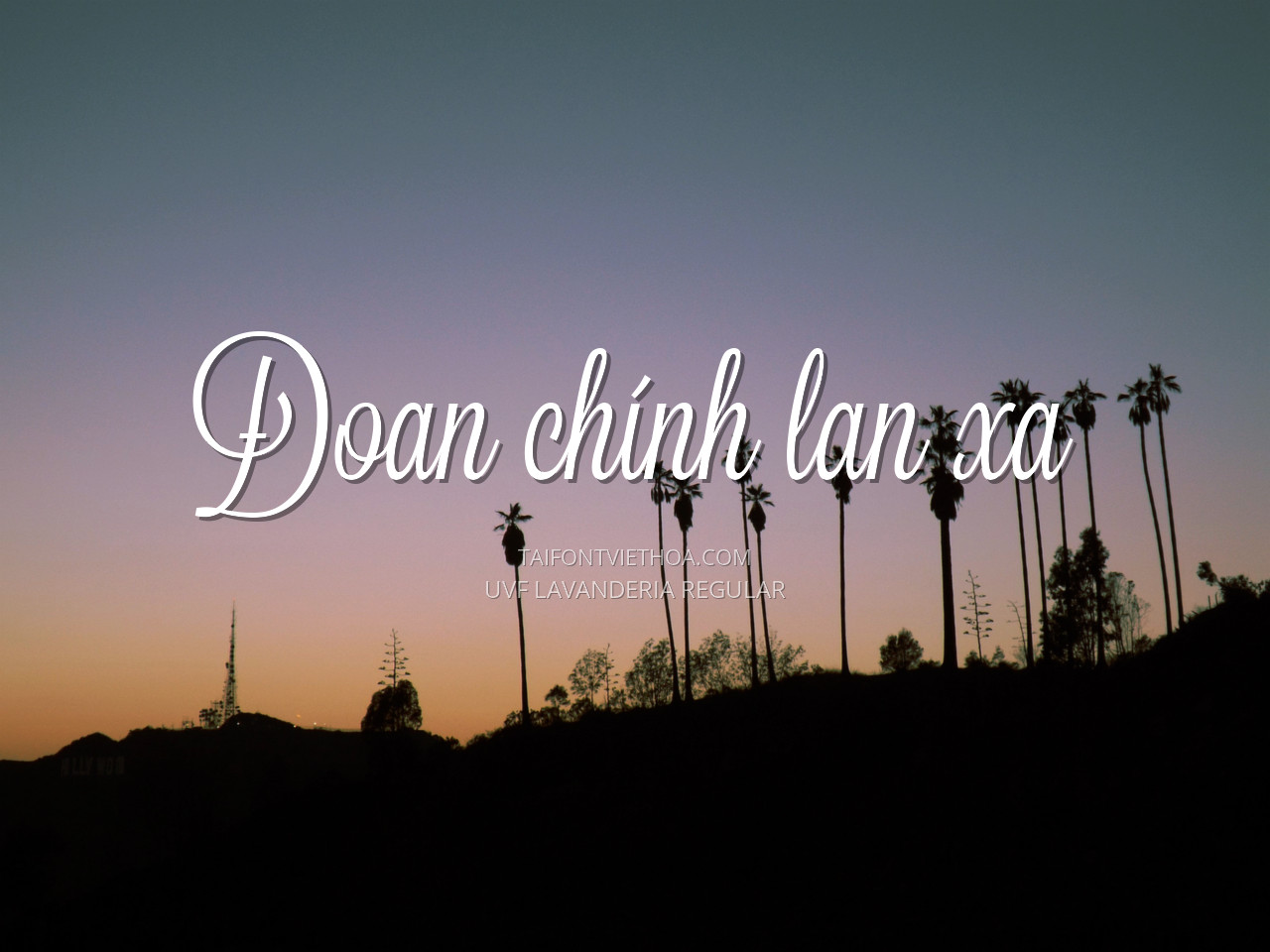
Font việt hóa UVF Lavanderia
Giới thiệu về font UVF Lavanderia
UVF Lavanderia là một kiểu chữ script lấy cảm hứng từ những bảng hiệu giặt là cổ điển ở khu Mission District, San Francisco. Font mang phong cách thư pháp hiện đại, với những đường nét lượn mềm mại, dứt khoát và duyên dáng. UVF Lavanderia đã được sưu tầm và chia sẻ bởi thành viên Font Chuẩn và được taifontviethoa.com chọn lọc để ứng dụng trong các dự án thương hiệu, in ấn cao cấp và thiết kế thiệp mời sang trọng. Font hỗ trợ đầy đủ tiếng Việt cùng hơn 200 ngôn ngữ khác, giúp mở rộng phạm vi ứng dụng trên toàn cầu.
Đặc điểm thiết kế và ứng dụng của UVF Lavanderia
UVF Lavanderia nổi bật với các ligature thanh lịch, cấu trúc chữ mềm mại và độ nghiêng vừa phải. Các nét chữ có sự đậm nhạt rõ ràng, tạo hiệu ứng thị giác mạnh mẽ khi sử dụng cho tiêu đề, logo hoặc in ấn nghệ thuật. Phong cách chữ viết tay của Lavanderia khiến nó trở thành lựa chọn lý tưởng cho các thiết kế mang tính cảm xúc hoặc cổ điển sang trọng.
Ứng dụng lý tưởng: thiết kế logo thương hiệu thời trang, mỹ phẩm cao cấp, bao bì sản phẩm handmade, bìa tạp chí, thiệp mời cưới hỏi hoặc ấn phẩm nghệ thuật cá nhân. Ngành nghề phù hợp: thời trang, làm đẹp, sự kiện, nghệ thuật sáng tạo, thương hiệu cá nhân và quảng cáo.